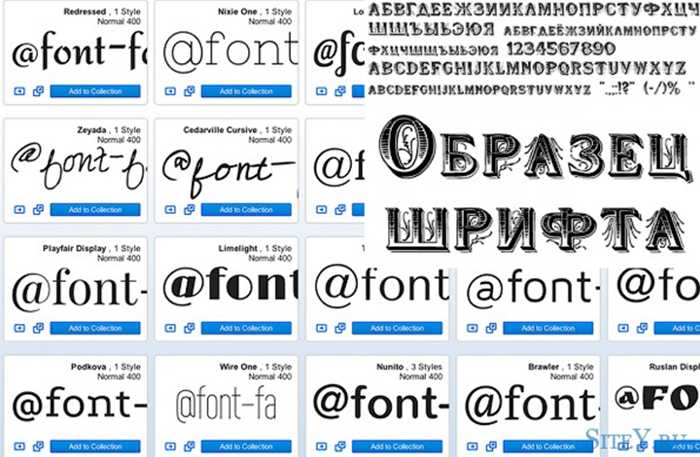
10 лучших шрифтов Google для ведения блога в 2023 году
В этой статье вы познакомитесь с лучшими шрифтами Google для ведения блога.
Неправильный выбор шрифта может передать неверное сообщение, вызвать усталость глаз и снизить вовлеченность в блог.
Выбор шрифта — это то, что многие владельцы блогов пренебрегают вниманием при настройке своих сайтов. Это особенно вредно в современном мире, поскольку большинство читателей наглядны.
Даже если у вас отличный контент, выбор подходящего шрифта может означать разницу между высоким удержанием читателей и высоким показателем отказов.
Когда дело доходит до трафика, то, что вы говорите, так же важно, как и то, как вы это говорите, и выбор подходящего шрифта имеет решающее значение.
Давайте подробнее рассмотрим значение шрифтов в блогах.
Как шрифт может улучшить читаемость?Неудивительно, что самые престижные газеты мира тщательно и целенаправленно выбирали стили шрифтов.
Даже самые мелкие детали могут легко отличить профессиональный веб-сайт от любительского блога для сегодняшних взыскательных читателей, а выбор шрифта — один из наиболее очевидных факторов.
Вот причины, по которым выбор правильного шрифта для блога имеет решающее значение для удобочитаемости.
Разные шрифты передают разные эмоции. В то время как шрифты с засечками ассоциируются с традициями, уважением и надежностью, шрифты без засечек ассоциируются со стабильностью и объективностью. Если вы открываете юридическую фирму, шрифты с засечками — хороший выбор.
Если вы ведете блог о свадебной фотографии, вам следует выбирать шрифты script или sans serif. Репутация компании может быть испорчена из-за неправильного шрифта.
Можете ли вы представить себе, что основной шрифт блога юридической фирмы Comic Sans?
Кто является целевой аудиторией вашего блога? Размер шрифта в блоге важен по разным причинам. Крупные шрифты и базовые гарнитуры помогают вести блог со старыми пользователями, потому что они облегчают им чтение вашего текста.
Наконец, нам также нужно скопировать и вставить правила CSS в ваш файл CSS. Если вы добавляете один шрифт Google для своего веб-сайта, вы можете добавить правила семейства шрифтов CSS в свой тег body. В противном случае вам нужно будет убедиться, что вы добавляете его к правильным элементам в ваших файлах CSS.